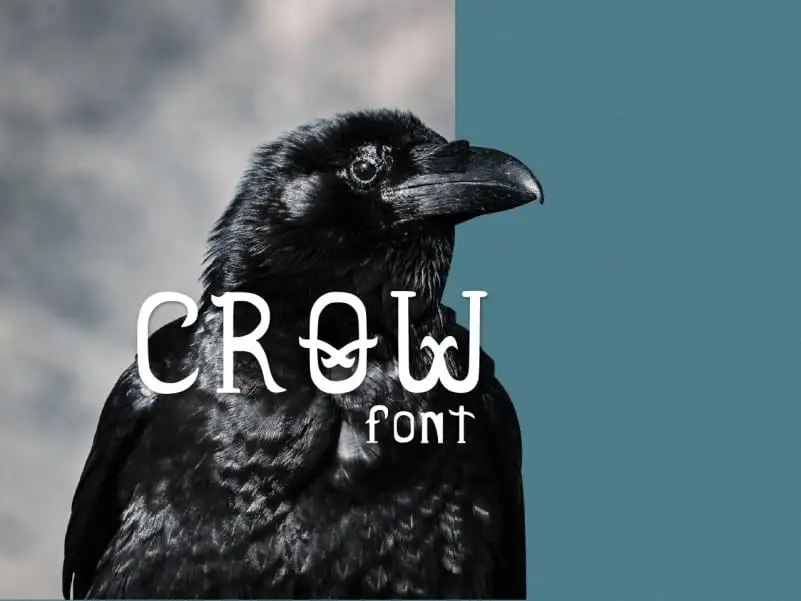
Crow Display Font – Download Grátis
A fonte Crow Display Font é inspirada nas alegres corvos do campo, com seus detalhes que lembram silhuetas deste animal elegante. Seu design gótico leva uma textura vintage, ideal para projetos variados como logos, tipografia, marcações e embalagens. Com sua estrutura única e características distintivas, essa fonte é perfeita tanto para quem busca um toque único em seu projeto quanto para aquelas empresas que valorizam uma dose de estilo antigo em suas identidades digitais. Seja você criando um rótulo de produto ou desenvolvendo a nova logomarca da sua marca, Crow Display Font certamente enriquecerá qualquer projeto em que ela seja utilizada.